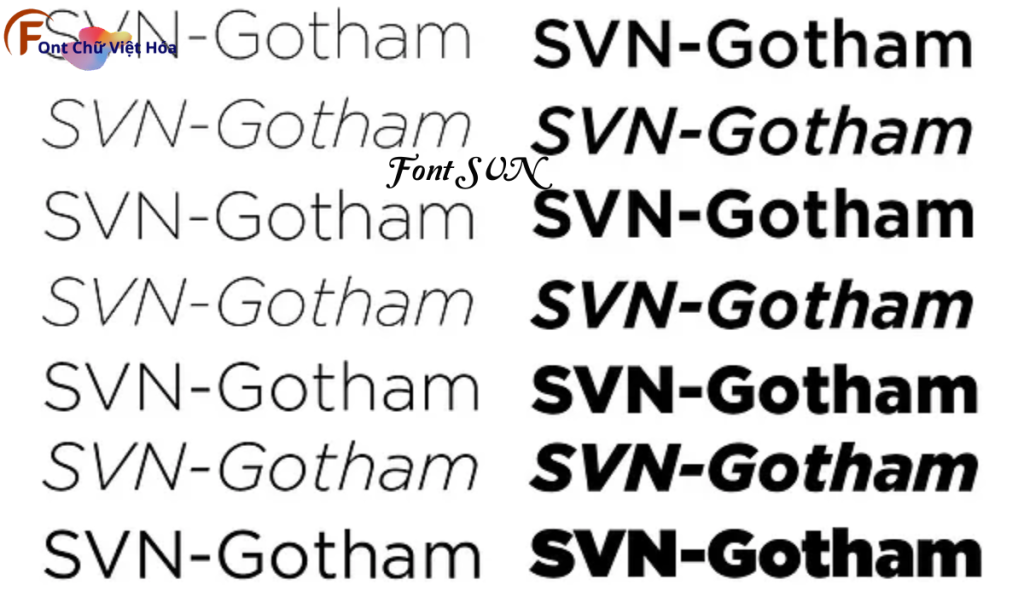
Font SVN Gotham Việt Hóa
Phân loại: Cá tính, Hiện đại
Độ dày: Nhiều độ dày
Font SVN Gotham Việt Hóa là một font chữ không chân hiện đại, thuộc bộ font SVN. Được thiết kế bởi Tobias Frere-Jones vào năm 2000, font này nổi bật với sự mạnh mẽ và rõ ràng, lấy cảm hứng từ các biển hiệu giữa thế kỷ XX tại New York. Font này đã được sử dụng rộng rãi trong nhiều chiến dịch, bao gồm cả chiến dịch tranh cử của Barack Obama năm 2008. Việc Việt hóa font giúp người dùng dễ dàng sử dụng trong các thiết kế tiếng Việt, mang lại sự tiện lợi và thẩm mỹ cao.